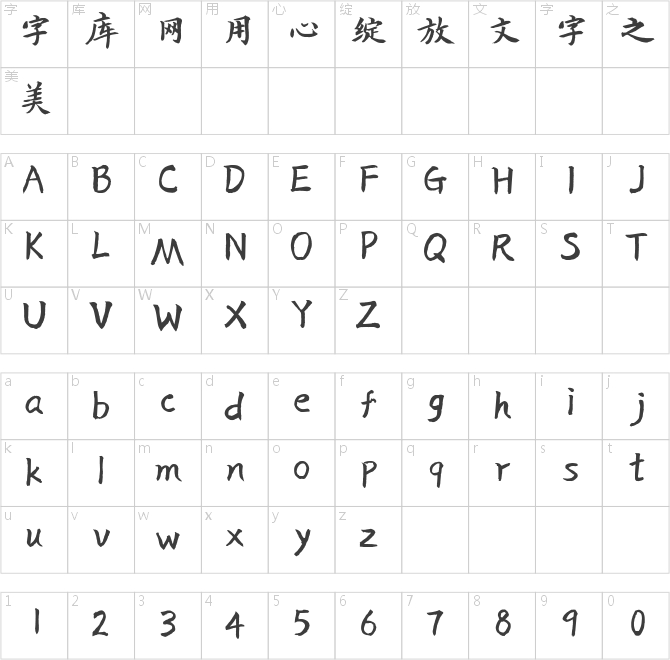
執(zhí)筆經(jīng)年不負(fù)卿
執(zhí)筆經(jīng)年不負(fù)卿字體字庫(kù)是一款讓人賞心悅目、百看不厭的中文字體,適合各類(lèi)廣告和產(chǎn)品包裝設(shè)計(jì)應(yīng)用,字體大小10.55MB,格式為ttf字體,上傳用戶是文道字庫(kù),作者/版權(quán)方為文道字庫(kù)